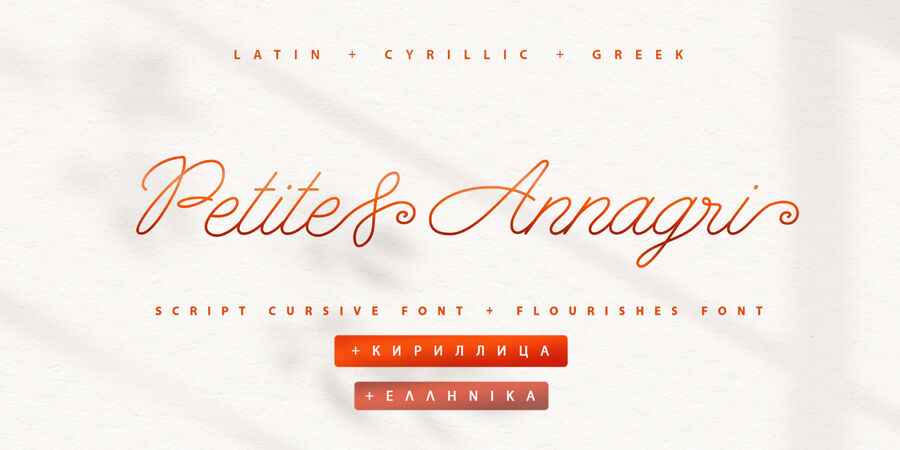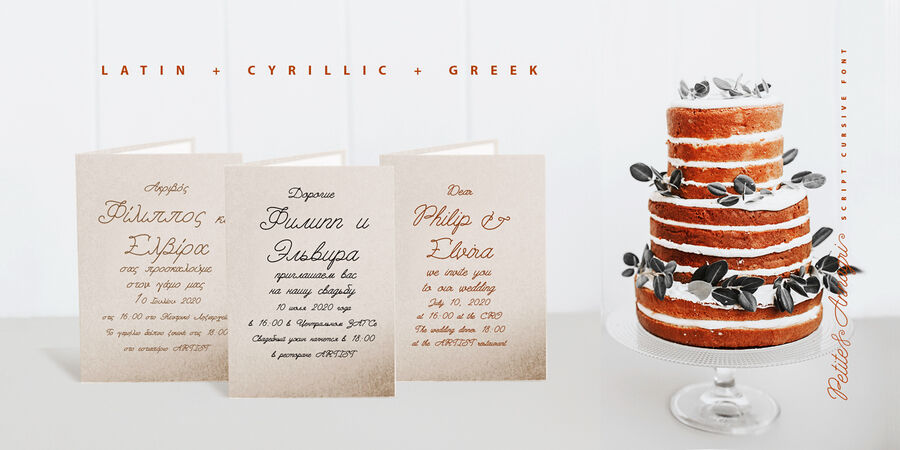
Petite Annagri Cyrillic (2 шрифта)
Опис гарнітури Petite Annagri CyrillicШрифтова пара Petite Annagri з підтримкою кирилиці та грецької мови + символьне накреслення допоможуть вам створювати вишуканий дизайн для весільної поліграфії, монолінійні логотипи з завитками та вензелями, любовні листи, цитати в інстаграмі, візитки, упаковку.
Petite Annagri Cyrillic Script включає набір великих і рядкових літер, цифр і великий діапазон розділових знаків. Petite Annagri symbols містить понад 36 монолайн завитків, розчерків та вензелів, елементів, ілюстрацій та штрихів, які допоможуть зробити ваш дизайн більш оригінальним. Щоб обрати потрібний елемент дивіться таблицю гліфів.
Багатомовна підтримка 33 мов на латиниці, підтримка кирилиці для української, російської, білоруської, болгарської та казахської мов, а також грецьку мову.
Шрифт розробила Ірина Двілюк у 2021 році.
Асоціації з сімейством шрифтів Petite Annagri CyrillicОсобистість і характер гарнітури:
дівчачий, казковий, наївний, новорічний, чарівний, милий, інтимний, крихкий, поетичний, артистичний, елегантний, весняний, святковий, доброзичливий, красивий, гарненький, симпатичний, крафтовий, артізанальний, радісний, свіжий, тонкий, повітряний, динамічний, натхненний, ліричний, чуттєвий, емоційний, музичний, творчий, гнучкий, оригінальний, самобутній, колоритний, живий, прозорий, характерний, весільний, романтичний, ритмічний, епістолярний, рослинний, домашній, ніжний, легкий, дитячий